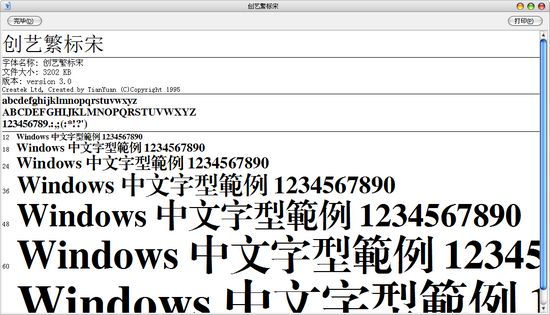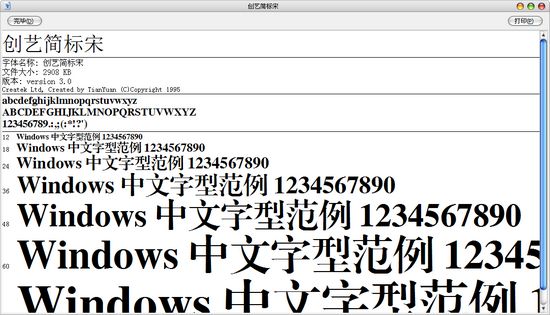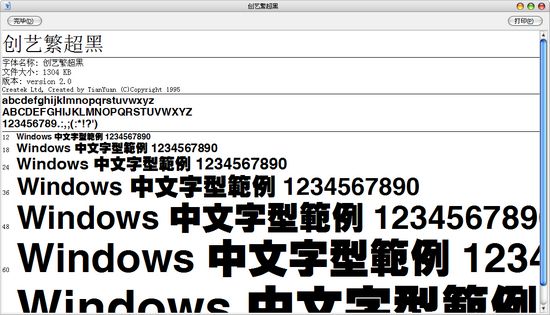
創(chuàng)藝字體包是一款字體打包軟件,中英語(yǔ)都有的該創(chuàng)藝字庫(kù)大全包含創(chuàng)藝繁標(biāo)宋、創(chuàng)藝間標(biāo)宋、創(chuàng)藝繁超黑、創(chuàng)藝簡(jiǎn)粗黑、創(chuàng)藝繁粗圓、創(chuàng)藝繁仿宋、創(chuàng)藝簡(jiǎn)魏碑等系列字體,適合設(shè)計(jì)人員使用。